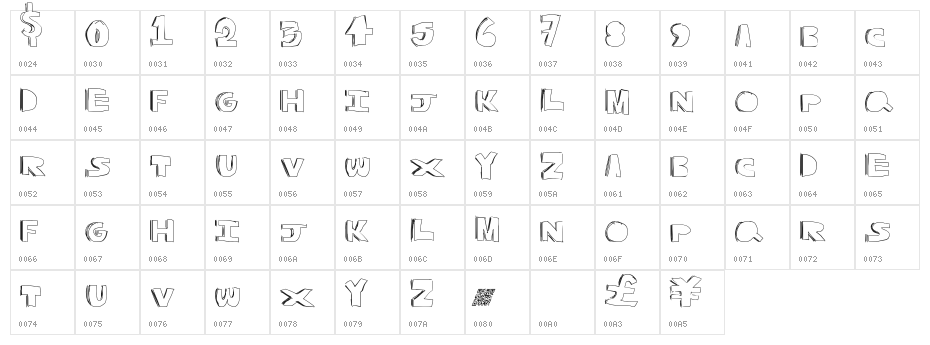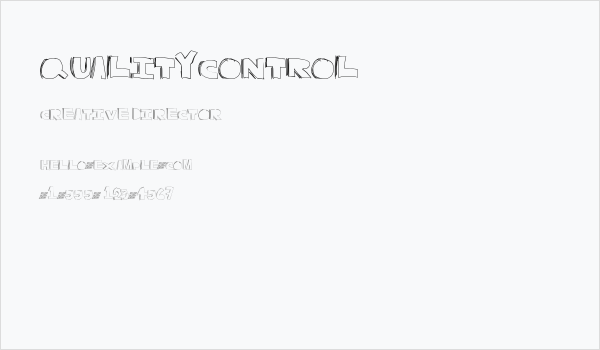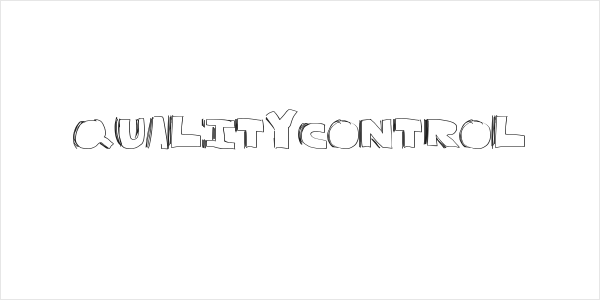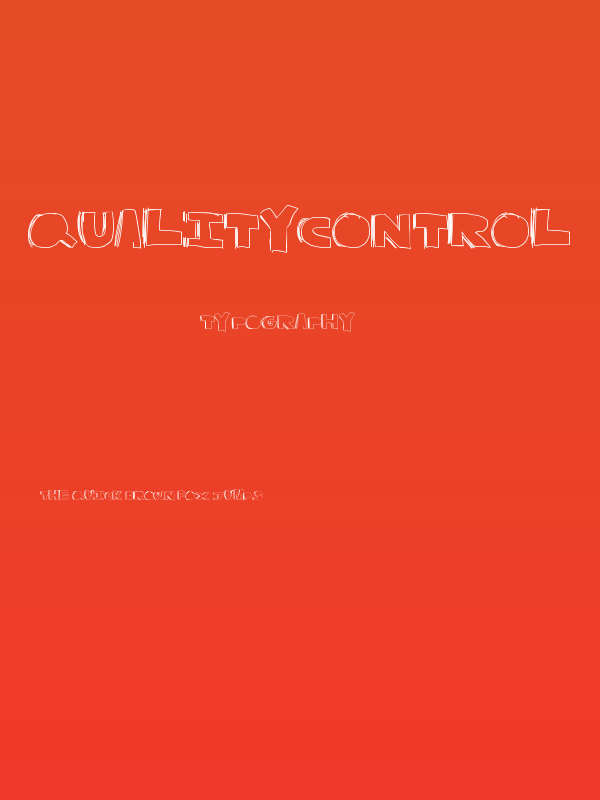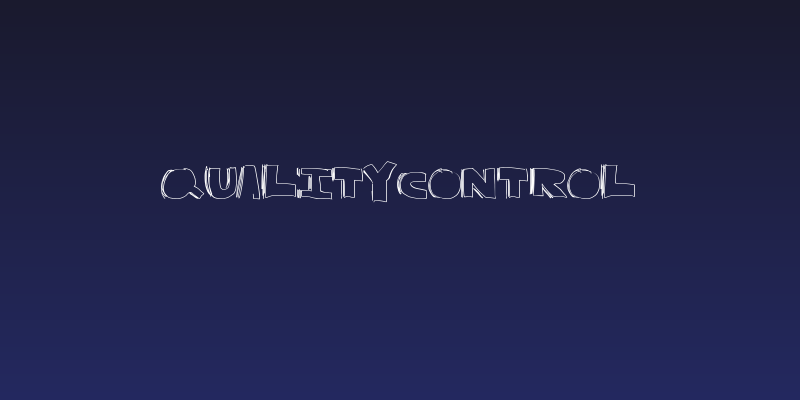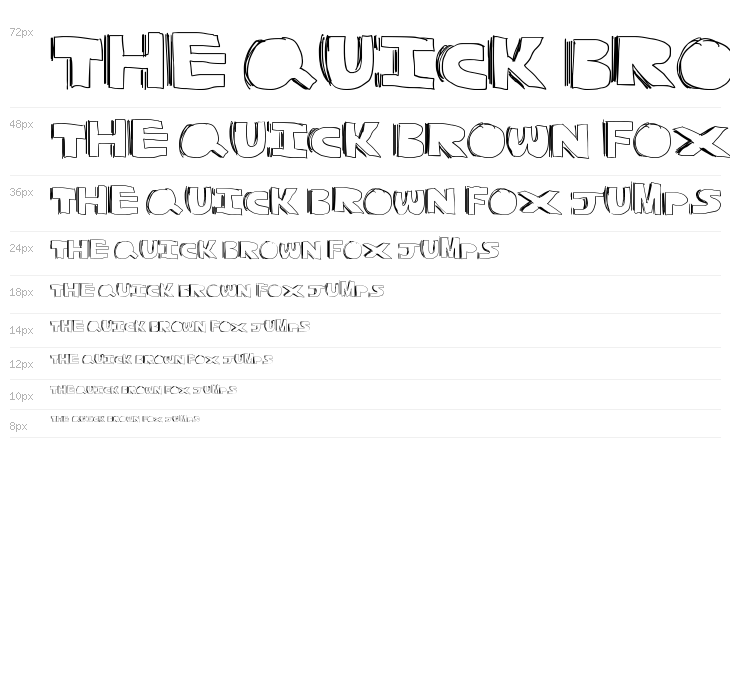
QualityControl Font
✎ Cartoon
| Gesamtstil | Playful, Creative, Dynamic |
| Vorgeschlagene Projekte | Ideal for comic books, children's books, playful branding, and creative posters. |